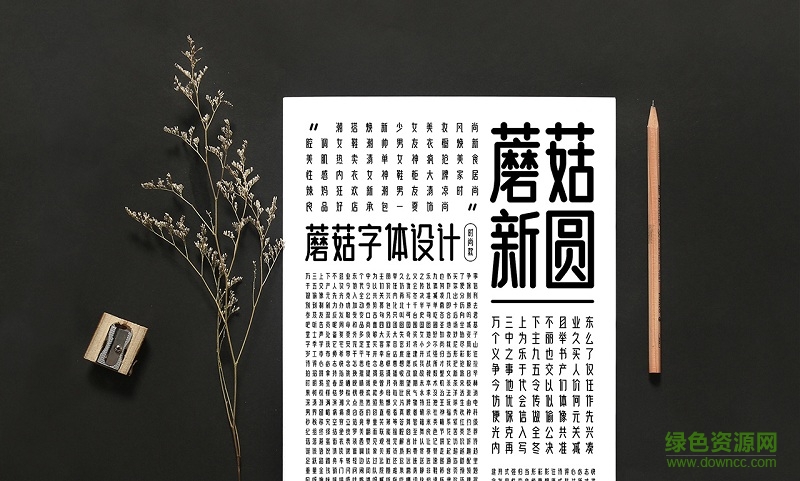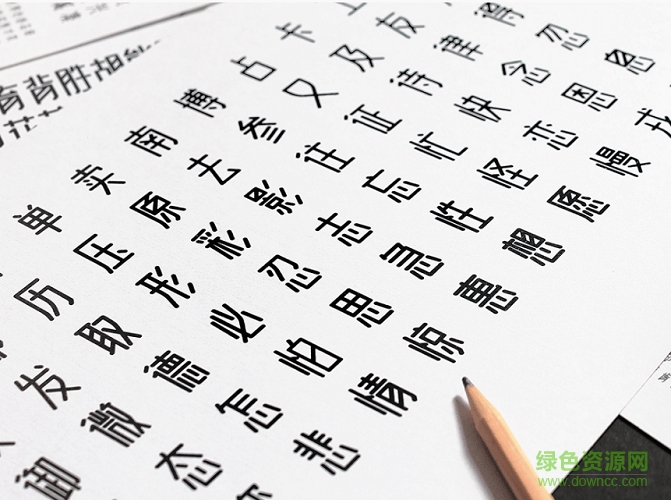
蘑菇新圓體是由MOGU FONTS推出的一款藝術字體,平滑的筆觸和溫和的棱角讓字體顯得更加時尚大方,尊崇于現代特色,給你最直接的視覺體驗,潮流百搭、平面設計都有獨特韻味,喜歡就來綠色資源網體驗吧!
蘑菇新圓體,所有的相遇都是久別重逢,致力藝術與商業(yè)的融合,用心書寫文字之美!
一撇一捺都是心血,一橫一豎都是藝術!
圓弧線:撇、勾進行特殊設計,兩圓相切的形式構造優(yōu)雅曲線,行筆圓滑,曲線柔美,給字體增添靈動感
角度:不斷的嘗試與優(yōu)化,將閉合空間里橫筆畫統(tǒng)一成40°最優(yōu)角度,讓平穩(wěn)結構的字產生新的律動
點括時尚風格:采用風格統(tǒng)一的「點」元素,一點成一字之規(guī),字距寬緊得宜,字形柔和纖細!
字形:黃金矩形結構,骨骼平和統(tǒng)一,筆畫勻稱。字形簡潔明快,規(guī)整不失柔美,線條清晰,呈現以現代感
源自現代設計:見字如面,如語傳情,承繼漢字之美,結合現代設計,探索視覺文字的多樣性!